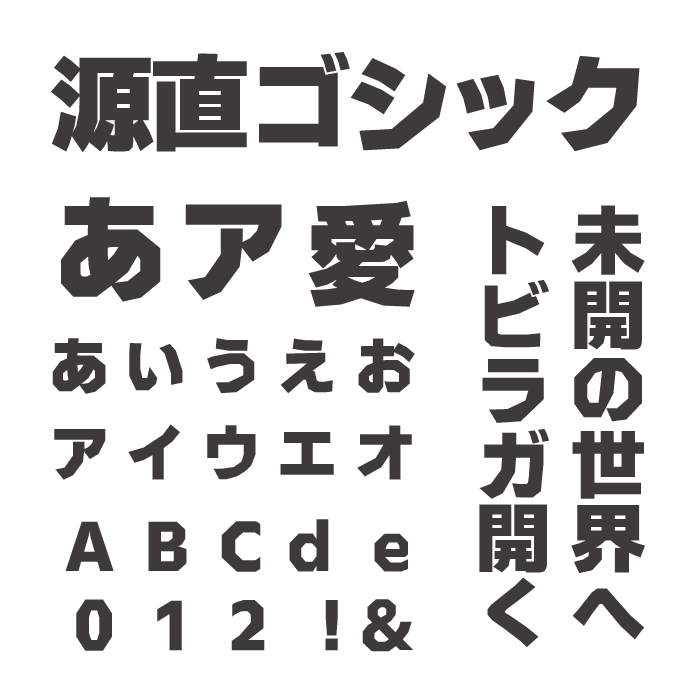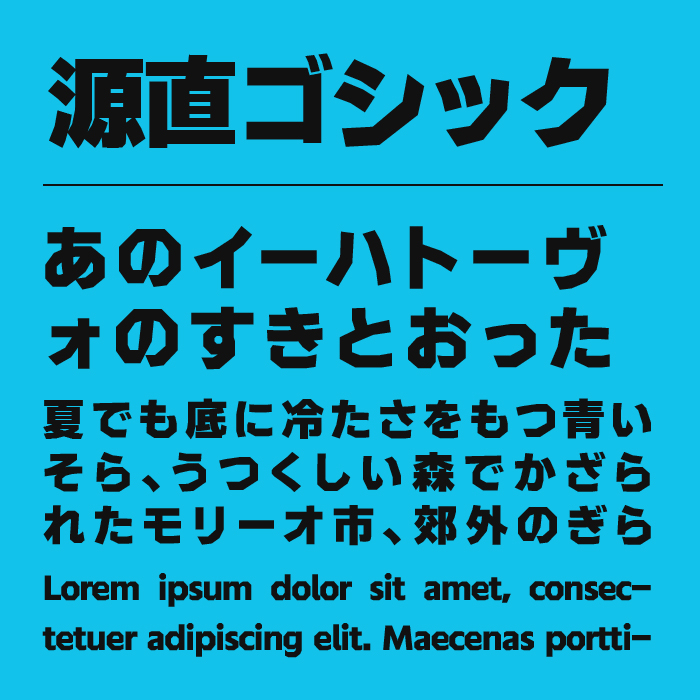
源直ゴシックフォントは、カクっとしており角が鋭く、ストレートな画線で構成された、硬派なゴシック体です。
一般的なゴシック体をカクカクとしたエフェクトで加工し、直線的で大胆なデザインが特徴なフォントです。
企業のキャッチコピー、ニュースサイトの見出し、建設業や製造業など信頼性と堅牢さが求められる分野のウェブサイトやパンフレットにぴったりなフォントです。装飾性がほとんどなく、純粋に文字の形だけで勝負しているため、「ごまかしのない、正直さ」を表現できます。
収録文字は、漢字・ひらがな・カタカナ・アルファベット・数字・記号が収録。